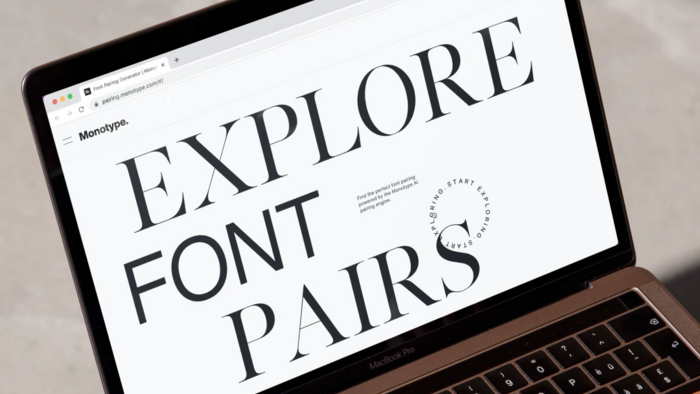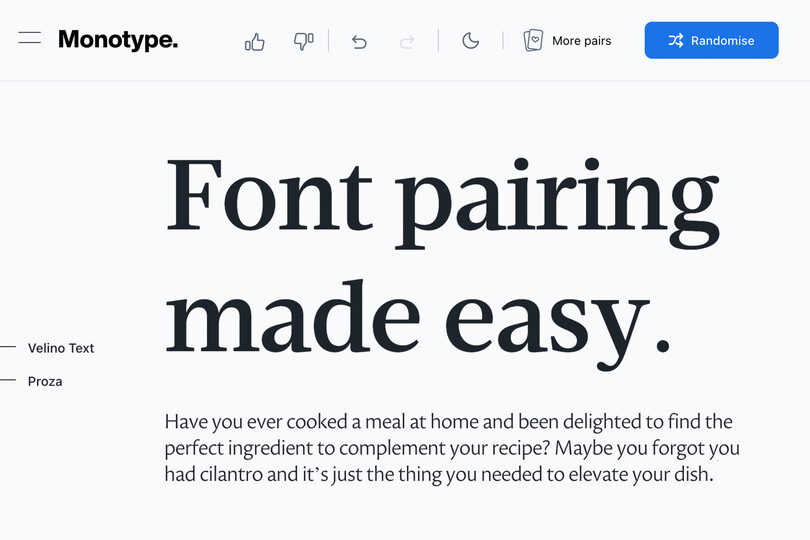
KI in Aktion: Die Magie des Schriftmischens.
Das Kombinieren von Schriften ist ein subjektiver Akt mit unendlich vielen Möglichkeiten. Aber wie wäre es, wenn Sie hierfür ein KI-Tool als persönlichen Assistenten hätten, der mit Ihrem Sachverstand und Ihren Emotionen das beste Ergebnis findet?
Haben Sie schon einmal ein Gericht gekocht und sich gefreut, die perfekte Zutat für Ihr Rezept in der Küche zu finden? Sie hatten längst vergessen, dass Sie Koriander, eine Biozitrone und eine Handvoll Erdnüsse  auf Vorrat haben … genau das, was Sie noch benötigen, um Ihr Gericht perfekt abzurunden.
Oder: Sie ziehen sich morgens für den Tag an. Ihre Lieblingsjeans liegen glücklicherweise frisch gewaschen im Schrank, aber Sie können sich für keines der Hemden entscheiden. Sie denken kurz an Ihre Stimmung und an die Fußwege, die Sie erwarten. Also greifen Sie zum flauschigen Kaschmirpulli und freuen sich auf die Stunden, die kommen.
In beiden Fällen haben Sie eine perfekte, maßgeschneiderte Lösung gefunden, besser als erwartet. Als Belohnung überkommt Sie ein Gefühl der Leichtigkeit, der Harmonie, das sie längere Zeit begleitet.
Genau so fühlt es sich an, wenn man die perfekte Schriftkombination gefunden hat.
„
Die perfekte Schriftkombination für Ihre Marke ergibt sich aus Ihrer Botschaft und Ihrer Schriftvorliebe. “
Terrance Weinzierl, Creative Type Director
The Monotype AI pairing engine.
Es ist eine von vielen täglichen Entscheidungen, bei denen Sie zwischen Harmonie und Kontrast abwägen.
Das Zusammenspiel von beidem führt zu durchdachten, sorgfältig komponierten Lösungen.
Wie das Kombinieren im Alltag ist es auch im Bereich der professionellen Typografie eine subjektive Angelegenheit mit unendlich vielen Wegen. Es gibt viele gute Lösungen, eine Menge schlechter, und einige wenige, die herausstechen.
Stellen Sie sich nun vor, Sie hätten ein KI-Tool als persönlichen Assistenten, der Ihr Know-how und Ihre Emotionen mit ins Spiel bringt? Es könnte Ihnen spannende, überraschende Ideen anbieten und gleichzeitig das Tempo und die Qualität Ihrer kreativen Entscheidungen steigern. Die Vorschläge könnten sogar als Resonanzboden oder Inspirationsquelle dienen. Und so nutzen wir Machine Learning, um die Tiefe und Breite unserer Ideen für Schriftkombinationen zu erhöhen.
Die Kraft der kombinatorischen Typografie.
Nehmen wir an, Sie entwickeln eine neue Zeitschrift. Bezüglich der Typografie liegt der Gedanke nahe, mit einer überschaubaren Palette von Fonts zu beginnen, zum Beispiel einer Sans- und einer Serif-Familie, die für den Fließtext zum Einsatz kommen sollen. Je nach Inhalt könnte für den einen Beitrag die Sans, für den anderen die Serif zum Einsatz kommen. Dieser praktische Kombinationsansatz kann sowohl Abwechslung als auch Geradlinigkeit ins Editorial Design bringen.
Die Kombination mehrerer Schriften erweitert Ihren typografischen Aktionsradius, weil sie mehr Optionen für die Hierarchie, den Grauwert, die Gewichtung sowie die Möglichkeit der tonalen Feinabstimmung bietet. Ein Beispiel aus dem Branding: Ein Arbeitstier aus dem Sans-Genre dürfte gut geeignet sein, fast alle typografischen Aufgaben einer Marke zu stemmen. Doch die schriftliche Kommunikation könnte mehr Emotionen ausstrahlen, wenn man sie mit einer gerundeten Sans kombiniert … oder persönlicher, wenn eine Script ins Spiel kommt. Oder sie könnte einen klassischen Ton anschlagen, wenn eine Serifenschrift das Repertoire ergänzt. Indem Sie eine einzigartige Schriftkombination finden, kann sich Ihre Font-Auswahl in ein spektakuläres typografisches Werkzeug verwandeln, das Sie mit einem Gefühl der Leichtigkeit und der Harmonie steuern.
Sicherlich kommen viele Marken und Projekte mit einer einzigen Schriftfamilie aus. Doch ein zweiter Schriftstil kann sowohl eine emotionale als auch eine technische Flexibilität in die visuelle Kommunikation einbringen – nicht zu verachten in der komplexen, digitalen Welt. Die ergänzende Schrift kann auch einen Weg ebnen, eine bestehende Marke zu erweitern oder aufzufrischen. Vielleicht wächst eine etablierte Marke durch einen neuen Produktbereich oder eine Dienstleistung, die eine andere Tonalität erfordert, aber gleichzeitig von der visuellen Nähe zur Muttermarke profitieren möchte … voilà: Eine Schriftpaarung ist die Lösung.
Schriftkombis sind äußerst wirkungsvoll: Sie sorgen für Abwechslung, Funktionalität und einen definierten Tonfall, der eine neue Marke belebt oder eine alte zum Leben erweckt.
Wie Schriften miteinander kombiniert werden: von Harmonie bis Kontrast.
Es gibt eine breite Palette von Schriftkombinationen, die von harmonisch bis kontrastierend reichen. Harmonisch bedeutet, dass die Konstruktion der Buchstaben in beiden Schriften ähnlich angelegt ist, sodass sie gut zusammenpassen, weil sie durch formale Eigenschaften miteinander verwandt sind. Ein blaues Hemd mit einer blauen Jeans, die sich farblich nur leicht unterscheiden, wäre eine harmonische Kombination. Eine Jeans mit einem orangen Hemd wäre ein kontrastreiches Paar. Kontrast heißt: Unterschiede betonen.
Meist führt die Kombination einer Sans mit einer anderen serifenlosen Schrift zu einer schwachen, und damit minimalen Differenzierung: viel Harmonie, wenig Divergenz. Für eine flexiblere typografische Palette wählen viele Designerinnen und Designer daher eine Serif-Sans-Kombination. Doch die Balance muss stimmen. So wie ein blaues Hemd mit blauem Jeansstoff zu harmonisch und langweilig wirken kann, könnte die Kombination Blau und Orange zu schrill sein und sehr bald die Augen strapazieren. In diesem Fall wäre ein Kompromiss in Form einer ähnlichen Farbe am besten, z. B. Grün oder Violett, die auf dem Farbkreis mit Blau verwandt sind: ein wenig Kontrast, doch überwiegend harmonisch. Das Spektrum der Schriftkombinationen funktioniert auf diese Weise ähnlich wie ein Farbkreis.
Unser Font-Pairing-Tool bietet Inspiration und Einblicke in die Kunst der Schriftkombination und hilft Ihnen, Ihre Schriftauswahl zu beschleunigen und zu verbessern. Das alles ist kein Zufall. Es ist Arbeit. Es geht um Schrift, Technologie und Expertise auf Knopfdruck.